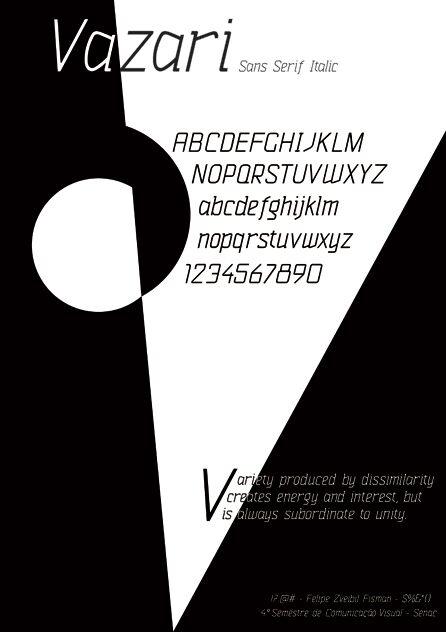
Vazari Sans Serif Italic von Felipe Zveibil Fisman ist eine kostenlose, humanistische kursive Sans-Serif mit einer leichten, handgeschriebenen Anmutung. Die Buchstaben wirken dynamisch und luftig, mit fließenden Kurven, offenen Formen und einem leicht kalligrafischen Schwung, der die Sans-Serif-Struktur auflockert.
Sie eignet sich hervorragend für Fashion-Snippets, redaktionelle Zwischenüberschriften, Boutique-Verpackungen, Buchtitel und Café-Branding, wo ein kostenloser Font für eine entspannte, kultivierte Stimmung sorgen soll. Nutzen Sie ihn für kurze Schlagzeilen, Titel oder Zitate, wenn Sie Bewegung wünschen, ohne dabei vollends auf eine Script-Schrift zu setzen – dank der Neigung und der weichen Formen erhalten selbst einfache Worte einen persönlichen Rhythmus.